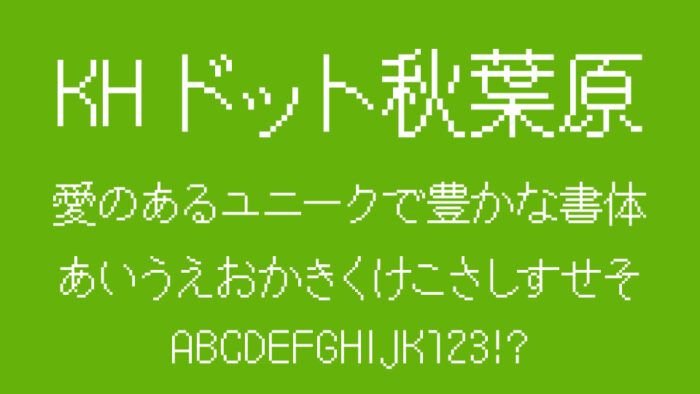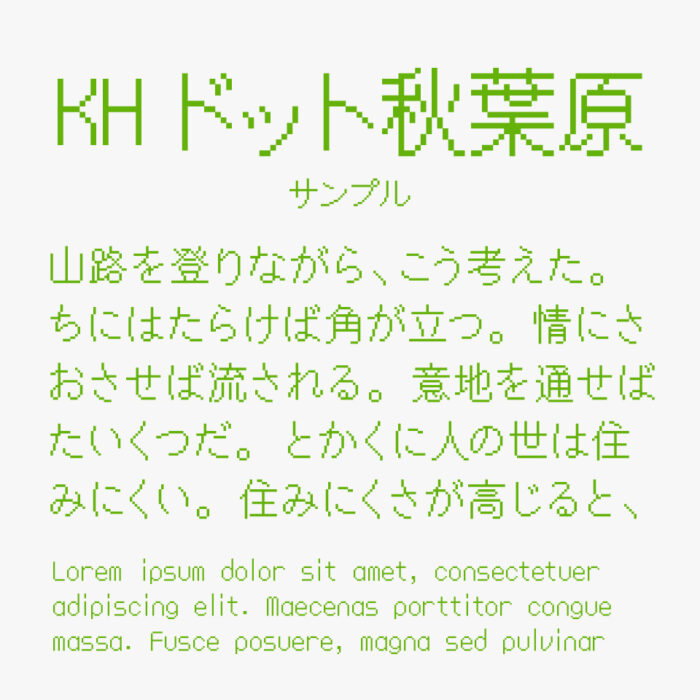
KHドット秋葉原
KHドット秋葉原フォントは、書体デザイナーの平木敬太郎氏が1991年から1996年にかけてリリースされたフォントを再構成したドットフォントです。
KHドットフォントは「KHドット道玄坂」「KHドット神楽坂」「KHドット日比谷」など地名を冠としてシリーズ展開されているドットフォントです。
その中でもKHドット秋葉原フォントは、丸ゴシックをベースとして作られているフォントです。丸みがある可愛らしい雰囲気をもつドットフォントです。